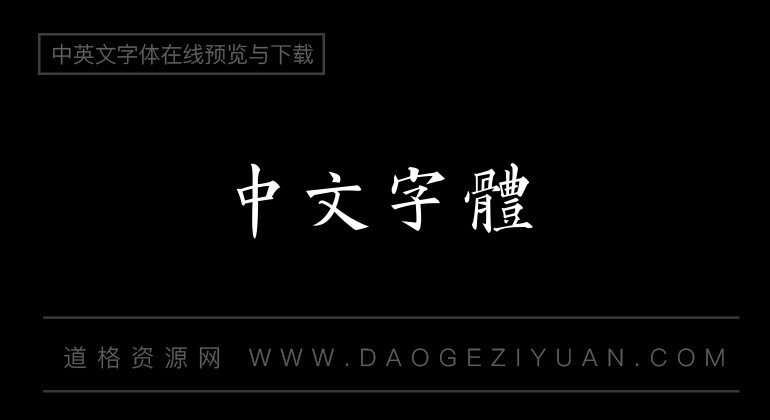
字酷堂黄自元楷体
字酷堂黄自元楷体是一款由字酷堂开发的中文字体,其字形设计结合了传统楷书精髓与当下流行的新颖元素,具有清新活泼、稳重大气的特点。字体拥有良好的可读性和清晰的字形,可以有效提升文档的可读性与视觉效果。此外,字体还支持多种字号,可以满足不同的使用场景。
字酷堂黄自元楷体是一款非常不错的手写艺术字体,具有很好的视觉感,适合于文化类的宣传设计、商业类品牌的广告和产品包装设计以及个性化文字排版等较多场景。